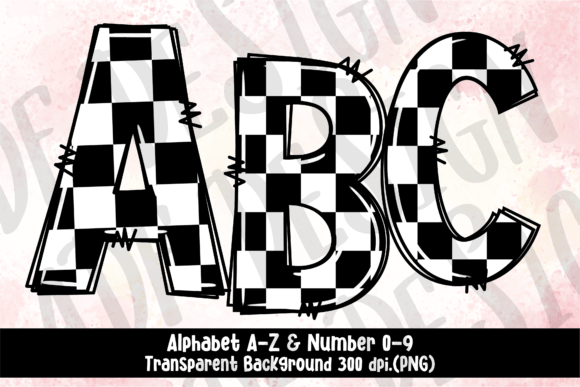
Checkered Doodle Alphabet Letters PNG
Trouver les bons éléments de conception peut être un défi, mais Checkered Doodle Alphabet Letters PNG propose une collection exceptionnelle qui rehausse instantanément votre travail.